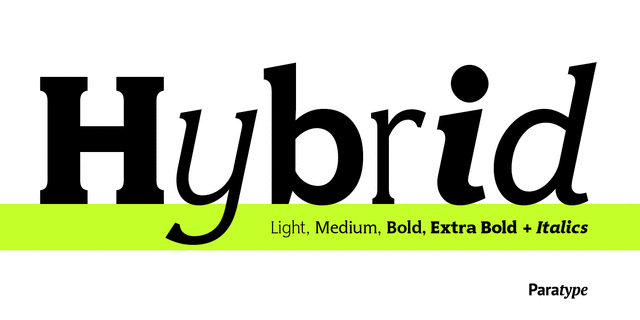
Шрифт разработан для фирмы ПараТайп в 1999-2003 годах (дизайнер Манвел Шмавонян). Малоконтрастная брусковая антиква с крупным очком строчных знаков и небольшими скругленными засечками. Предназначен для набора текста и акциденции. Благодаря открытому рисунку и большому количеству начертаний может хорошо сочетаться с открытыми гротесками гуманистического типа. Дизайн шрифта был отмечен специальным призом на конкурсе 'Кириллица'99'.
спокойный, ровный, уравновешенный, консервативный, ненавязчивый, умеренный, техничный, практичный, статичный, культурный, устойчивый, серьезный, качественный, убедительный, мотивирующий, ответственный, твердый, суровый, тяжелый, сильный, крепкий